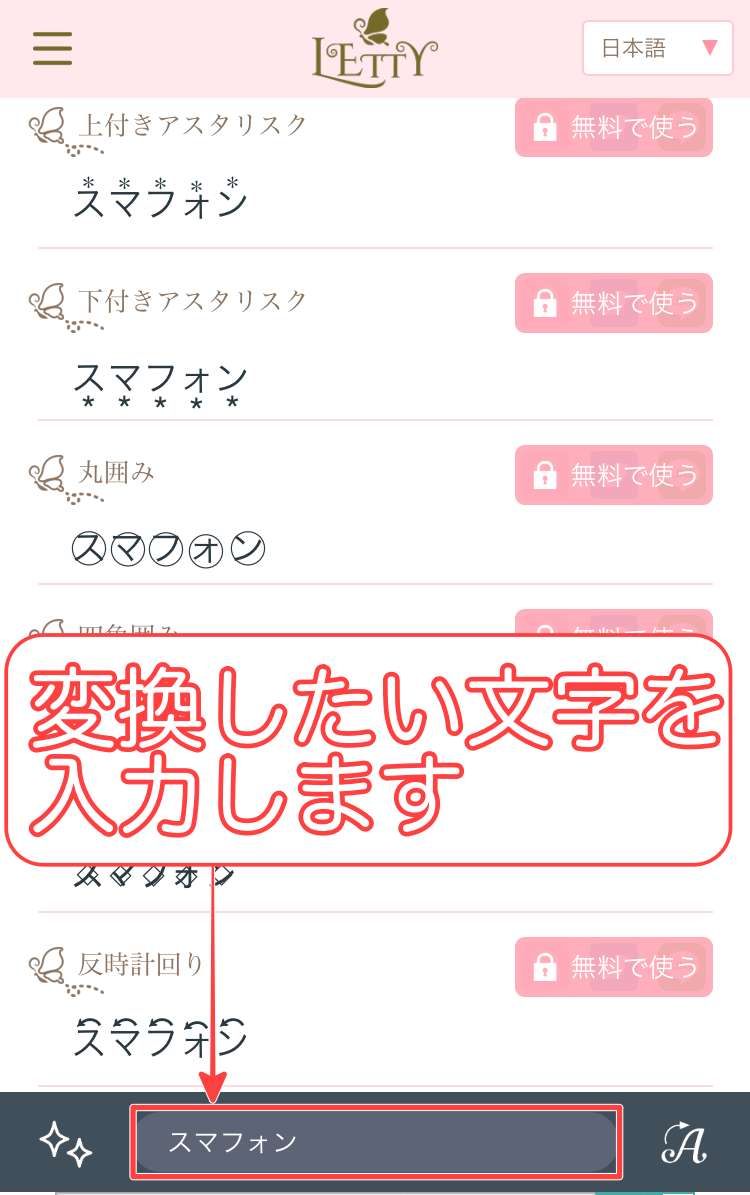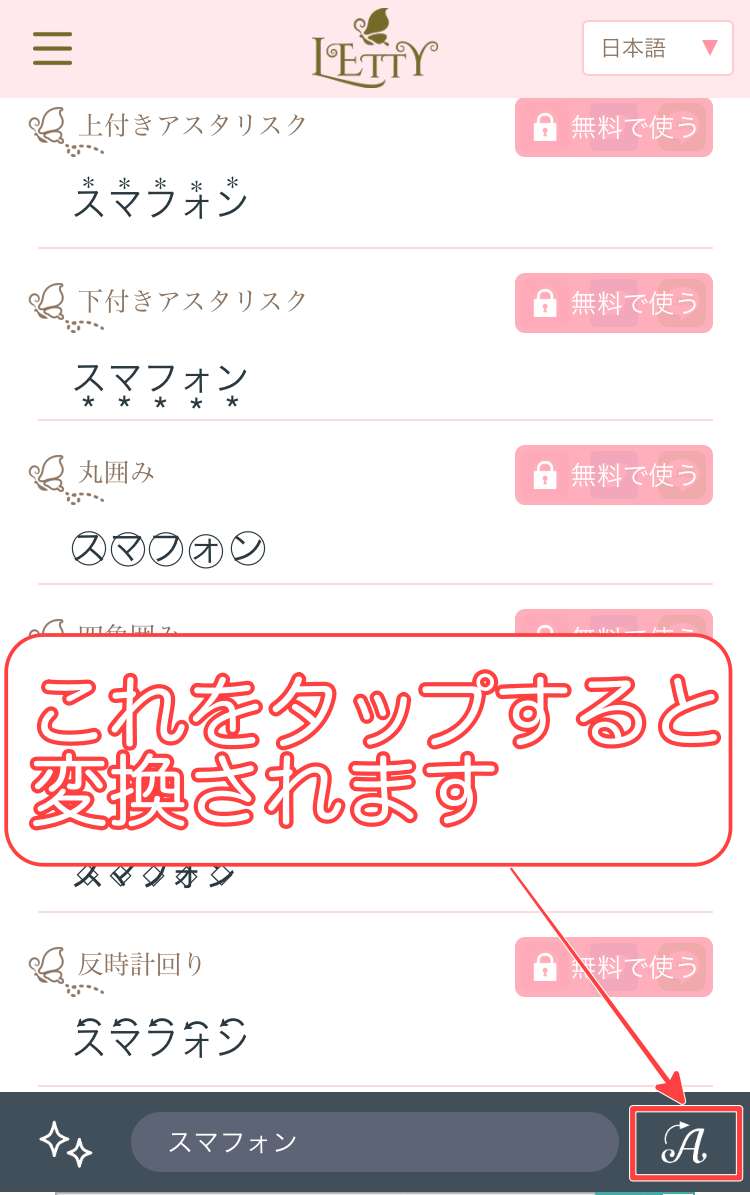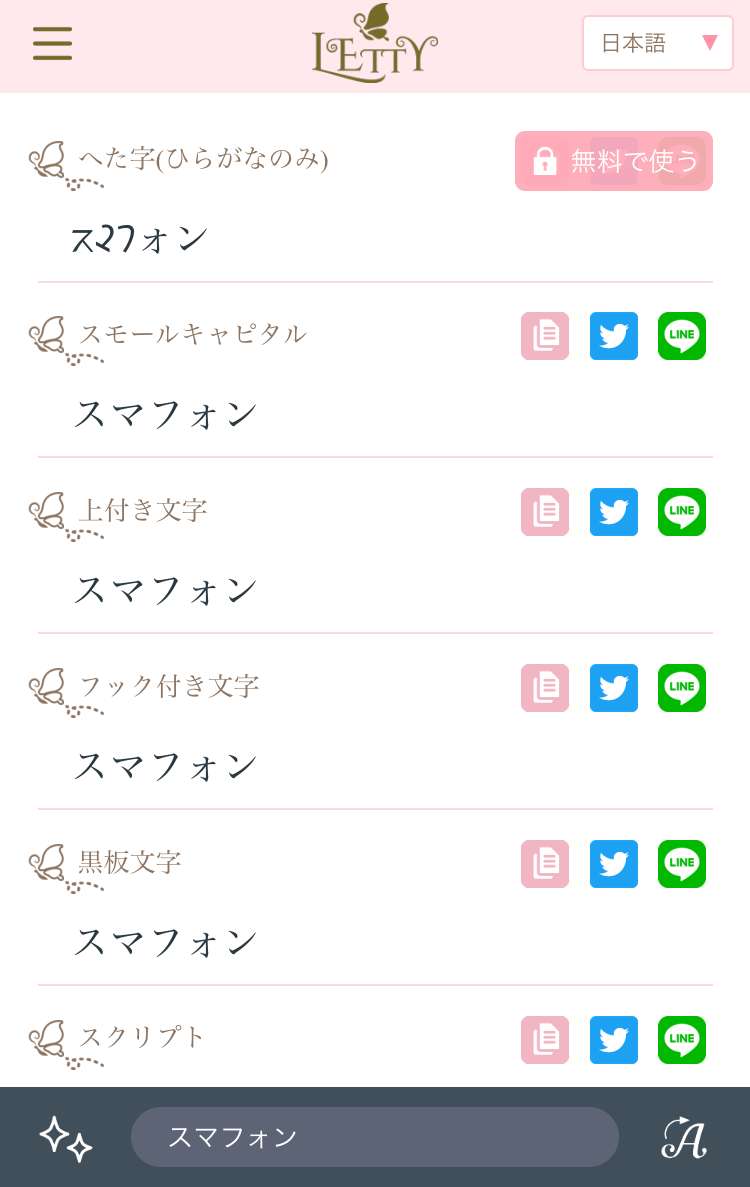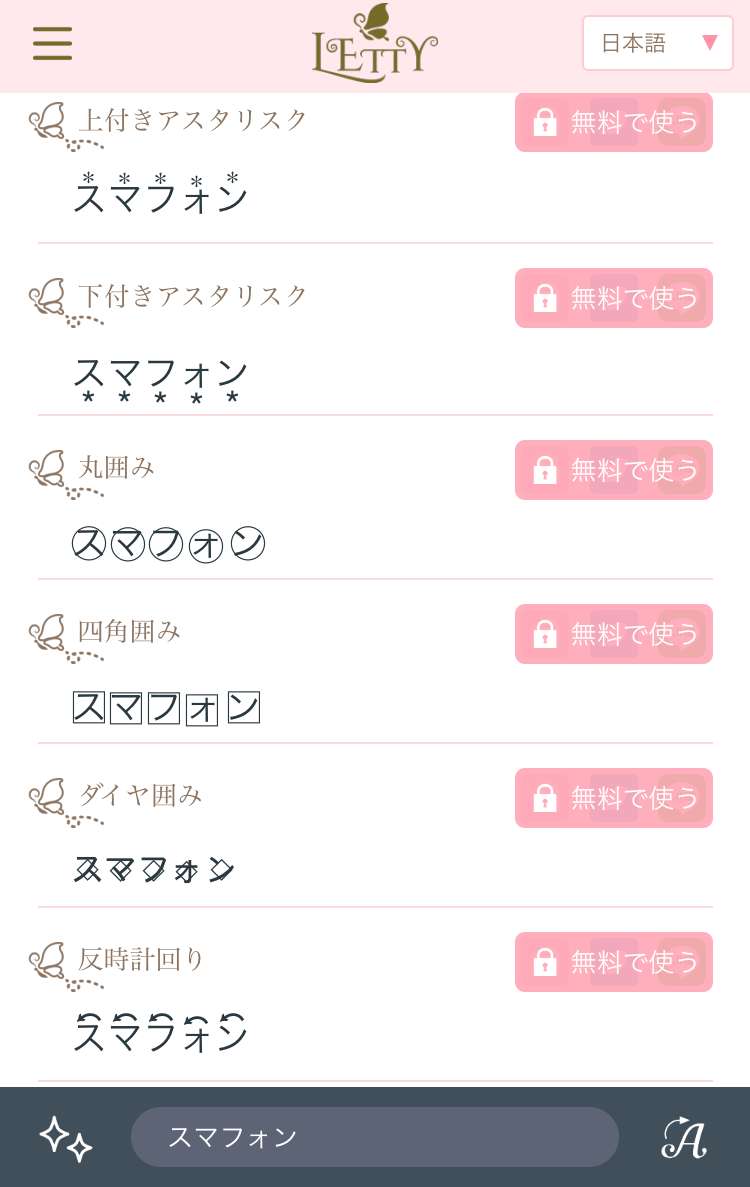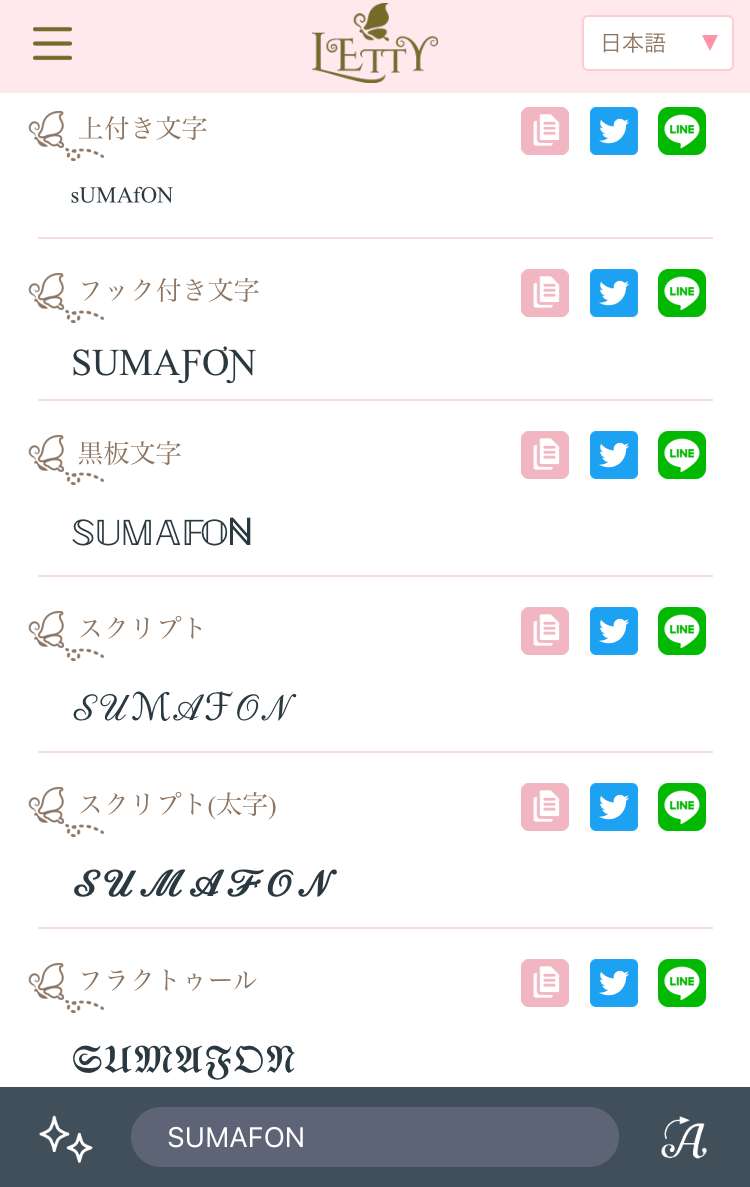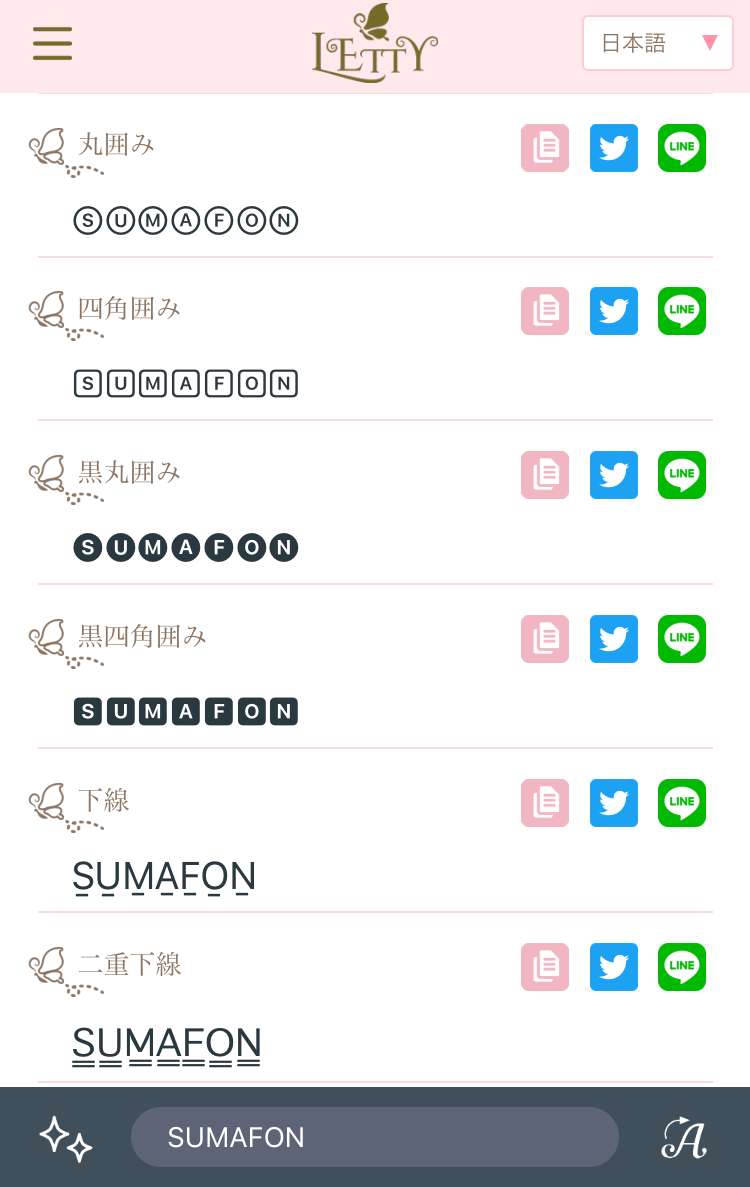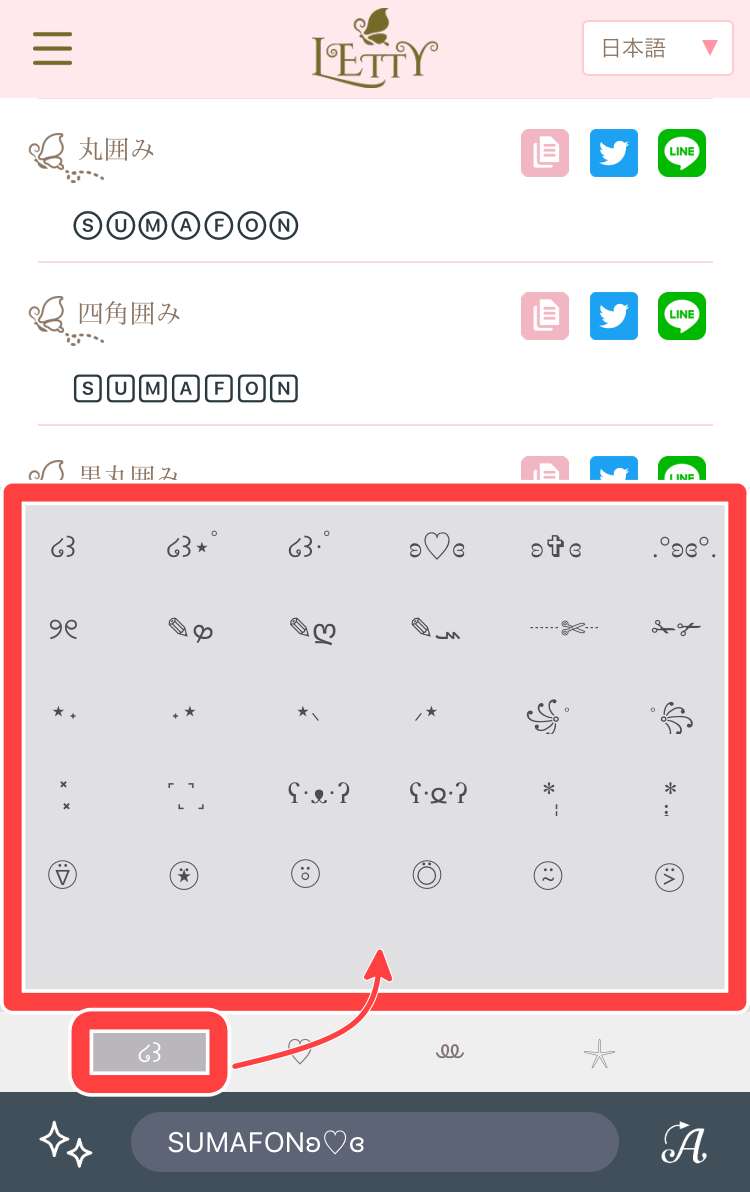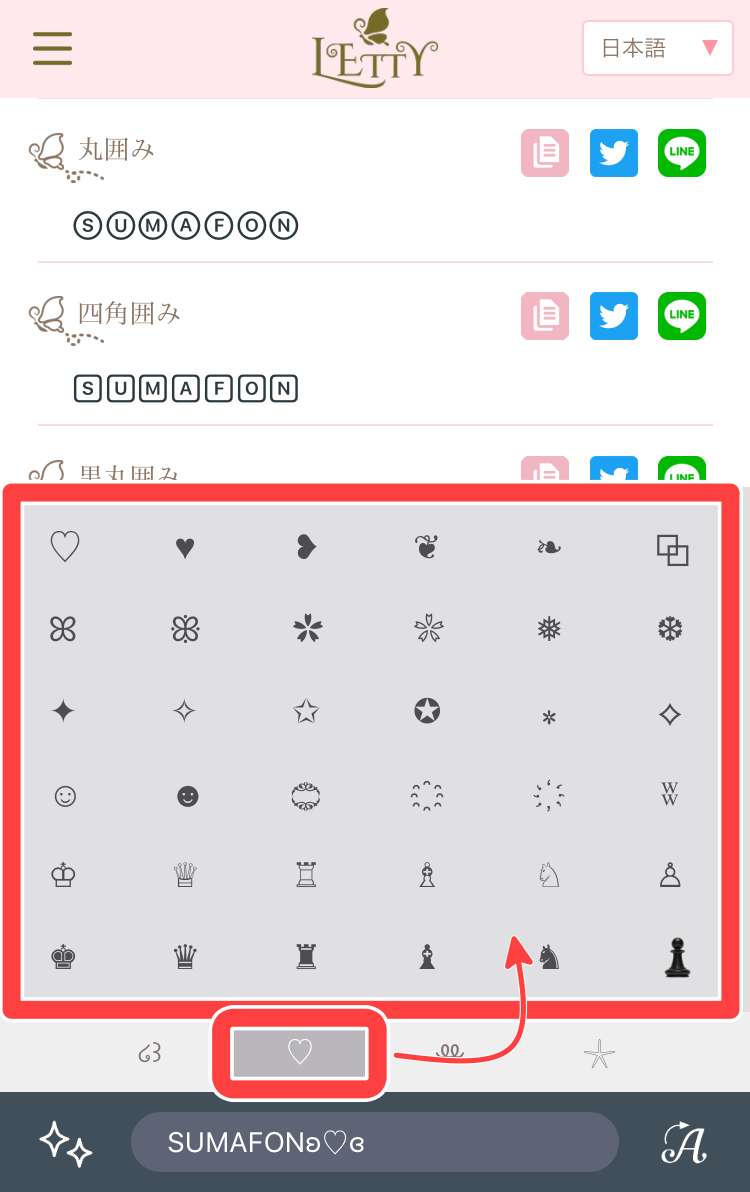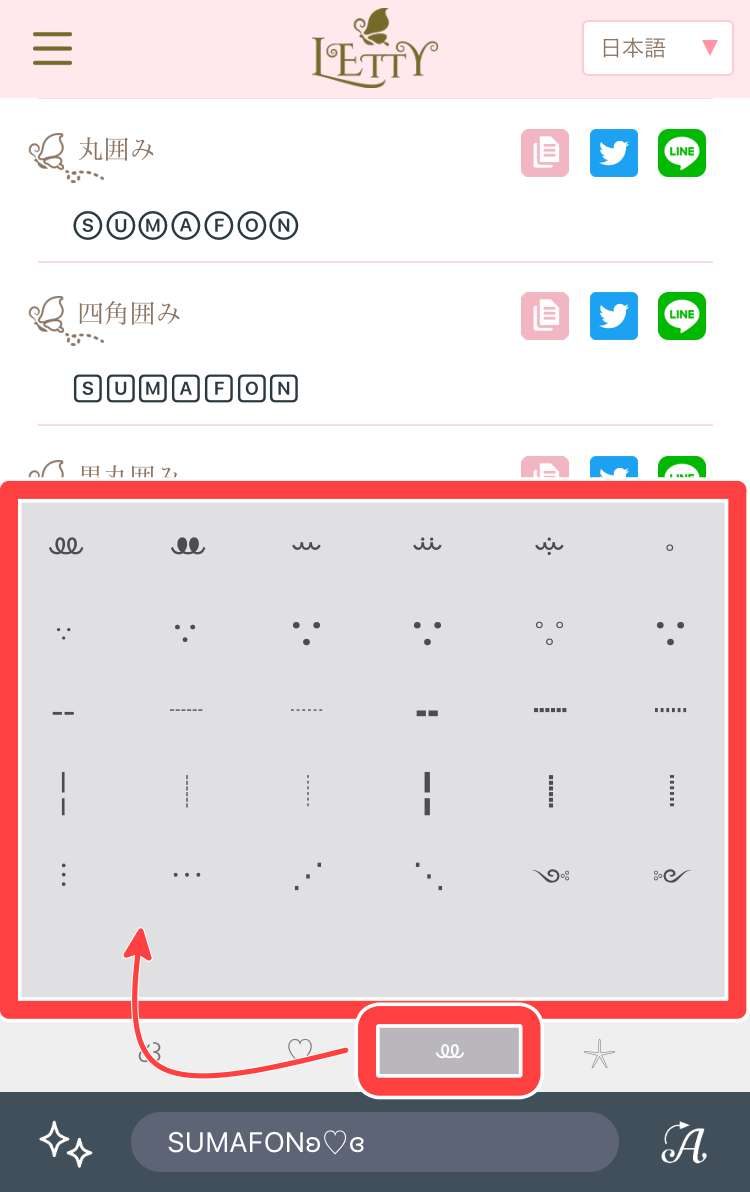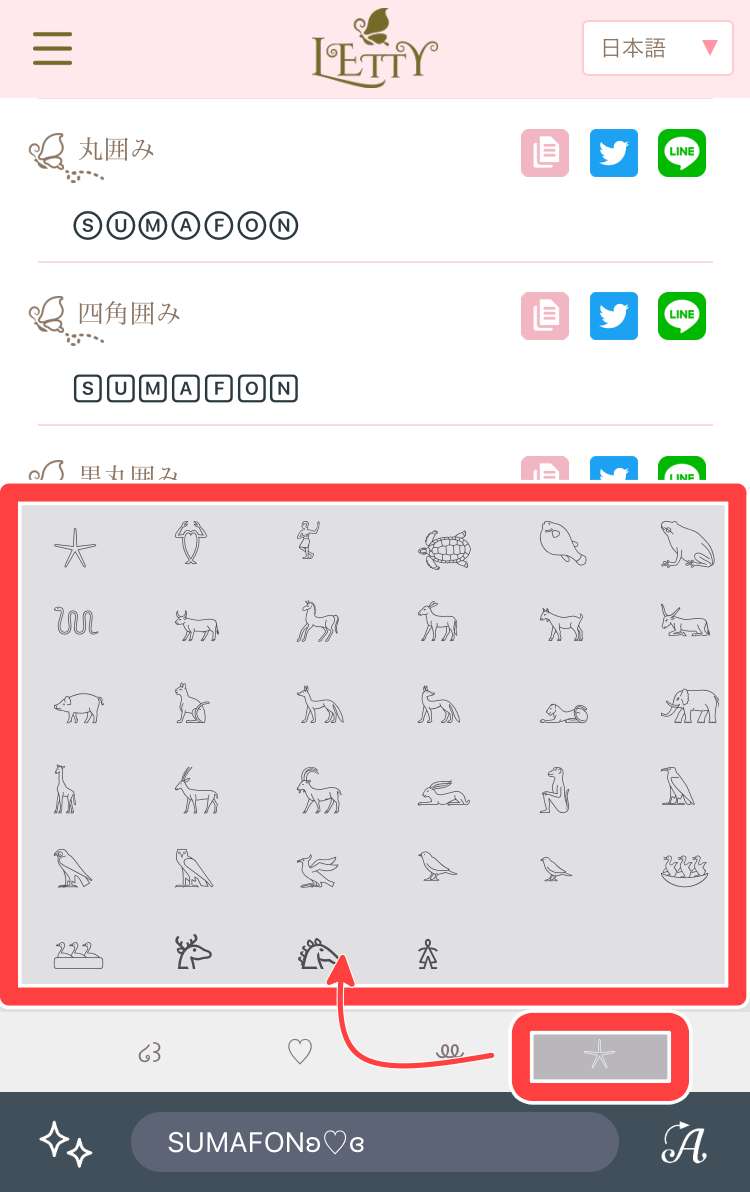
インスタグラムやTwitter、LINEのプロフィールで可愛い特殊文字(文字フォント)を使っている人も多いですよね。
あのおしゃれな文字フォントってどうやって作るの?
例えば、
の様な筆記体とか、
そうそう!これ!
こんなおしゃれで可愛い特殊文字のフォントがコピペで簡単に変換できるツール・サイトがあるので紹介したいと思います。
インスタグラムのプロフィールやコメントに使う事で、他とは違う貴方だけのオリジナルのプロフィールが出来るはずです。
インスタのプロフィールにおすすめの可愛い文字フォント
インスタなどのプロフィールに使用できる可愛い特殊文字をコピーするには、
- サイトでコピーする方法
- アプリを使って生成した特殊文字をコピーする方法
の2つがあります。
そこでこの記事では、
- 可愛い特殊文字を今すぐコピぺできるサイト:「LINGOJAM」
- 筆記体や可愛いフォント文字を選べるサイト:「PlainStyle」
- スマホにインストールして使えるアプリ:「LETTY(日本語対応)」
を紹介したいと思います。
どれもおしゃれで可愛い特殊文字が簡単にできるツールなので、ぜひ楽しんで作ってみて下さい^^
①:可愛い特殊文字を今すぐにコピぺできるサイト「LINGOJAM」
LINGOJAMの使い方はとっても簡単で、上のボックス内に変換したい文字を入力します。
すると下のボックス内に可愛い文字がズラ〜っと表示されます。
その中でお気に入りの特殊文字をタップしてコピーして、インスタグラムなどのプロフィールに貼り付けます。
【特殊文字の変換例】
②:筆記体や特殊なフォントを選べる「PlainStyle」
PlainStyleも簡単に筆記体や特殊な文字フォントに変換することが出来ます。
PlainStyleの特徴は、変換させたい文字を入力後、自分で文字フォントを選択できる点です。
変換できる文字フォントに限りはありますが、選択する楽しさもあるので、いろんなパターンを試したい人にはオススメのサイトです。
まず、ボックス内に特殊文字に変換させたい文字を入力します。
入力後、下の変換させたい特殊文字のフォントを選択してタップすると、上のボックス内に変換後の特殊文字が表示されます。
そこに表示された特殊文字をコピーしてインスタやTwitterなどで使用します。
③:Android・iPhoneにインストールして使えるアプリ「LETTY」
AndroidスマホやiPhoneにインストールする一手間はありますが、アプリとして利用するなら「LETTY」一択です。
「LETTY」の使い方も非常に簡単で、スマホさえあればいつでもどこでもおしゃれで可愛い特殊文字をアプリで生成することが出来ます。
画面の一番下にある入力窓に可愛い特殊文字に変換したい文字を入力して、右にある【A】をタップすると入力した文字がフォントごとに上の欄に表示されます。
気に入った特殊文字があれば、文字フォントの右側のコピーマークをタップするとクリップボードにコピーされます。
コピー後はインスタグラムやTwitterなどに貼り付けます。
ちなみにTwitterマークやLINEマークをタップすると各SNSでシェアすることも出来ますよ。
また、「LETTY」の面白いところはこれだけではなく、文字以外の可愛い特殊文字も使えるという点。
例えば、画面下の文字入力窓の左側にある【☆】マークをタップすると以下の様な文字が表示されます。
その他にも、
面白くないですか?
先に紹介したサイトでは表示されなかった可愛い特殊文字も「LETTYなら入力することが出来ますよね。
そして入力が完了したら、
してインスタグラムやTwitter、LINEなどのプロフィールに貼り付けることが出来ます。
まとめ
今回はインスタプロフィールの文字フォントを可愛い【特殊文字】に変換!というテーマで可愛い特殊文字に変換できるサイトやアプリを紹介しました。
今すぐに特殊文字をコピーしたい場合は、
- 可愛い特殊文字を今すぐにコピーできるサイト「LINGOJAM」
- 筆記体や可愛いフォント文字を選べるサイト「PlainStyle」
がおすすめです。
日本語に対応した特殊文字やフォントが使いたい場合は、スマホにインストールして使えるアプリ「LETTY(日本語対応)」
がおすすめです。
ぜひ、あなたの使用用途にあったツールを選んで楽しく利用してみてくださいね。